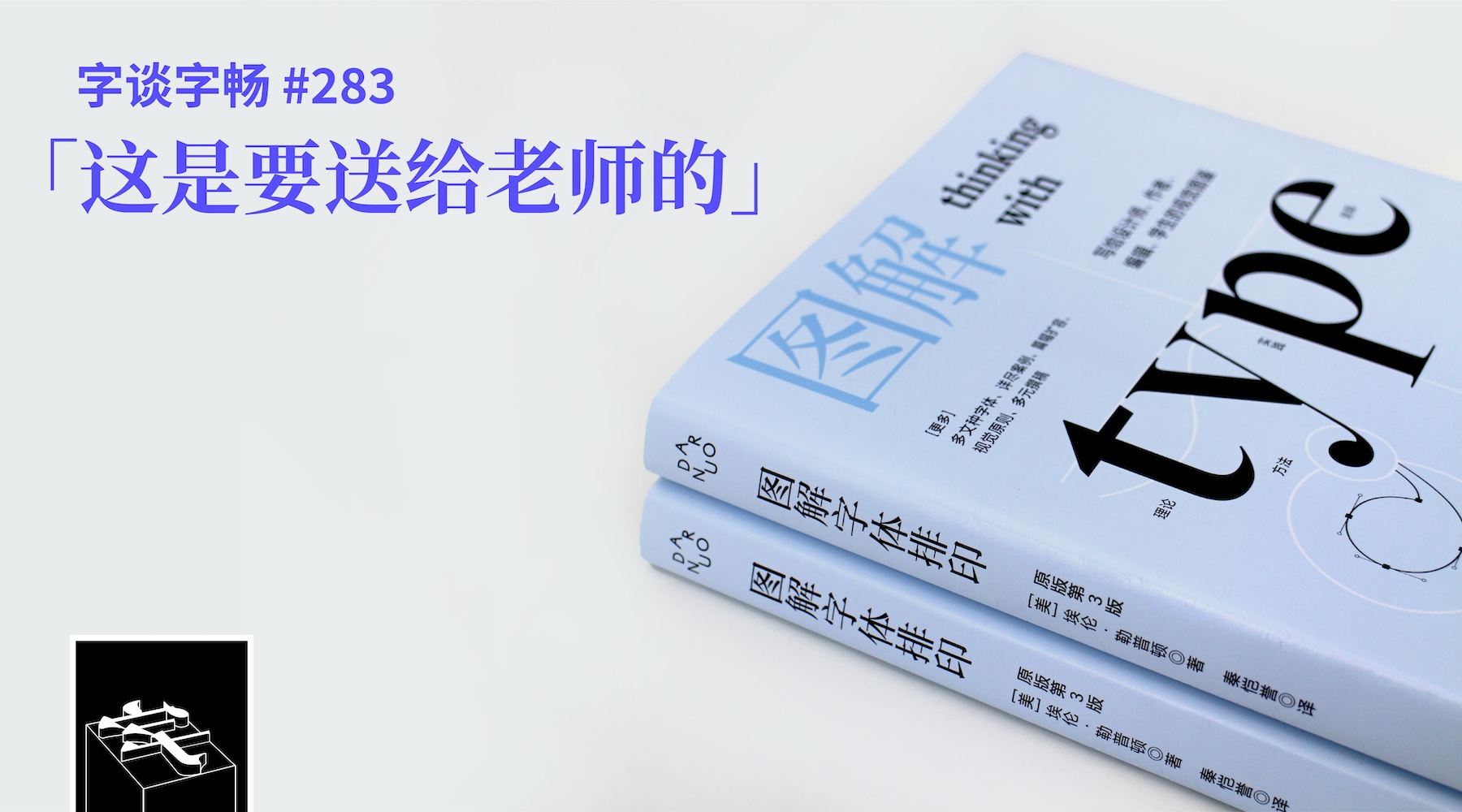
#283:「这是要送给老师的」
译著《图解字体排印》付梓面世。这是埃伦·勒普顿的畅销作 Thinking with Type 第二次翻译成简体中文。今天,我们有幸邀请到本书的编辑许梦蕾、设计师杨梓俊,与大家分享出版制作的幕后故事。
- Ellen Lupton. Thinking with Type: A Critical Guide for Designers, Writers, Editors, and Students. Princeton Architectural Press, 2004
- Ellen Lupton. Thinking with Type: A Critical Guide for Designers, Writers, Editors, & Students (2nd ed.). Princeton Architectural Press, 2010
- Ellen Lupton. Thinking with Type: A Critical Guide for Designers, Writers, Editors, and Students (3rd ed.). Princeton Architectural Press, 2024
- 埃伦·鲁普顿(著)、王毅(译).《字体设计指南》.上海人民美术出版社,2006 年
- 埃伦·勒普顿(著)、秦恺誉(译).《图解字体排印》 .上海人民美术出版社,2026 年
- 艾琳·路佩登(著)、 林庭如(译).《圖解字型思考指南:從字體到版型,從平面到數位,寫給設計師、寫作者、編輯與學生的必修經典》 .商周出版,2026 年
- Ellen Lupton,美国知名平面设计师、策展人、作者、教育者,2007 年获 AIGA 奖章
- Signifier,西文衬线字体家族,Klim Type Foundry 出品
- FT Thymes,西文衬线字体家族,何诗旸设计,方正字库出品
- 阿德拉姆字母(Adlam),用于书写富拉语(Fula)